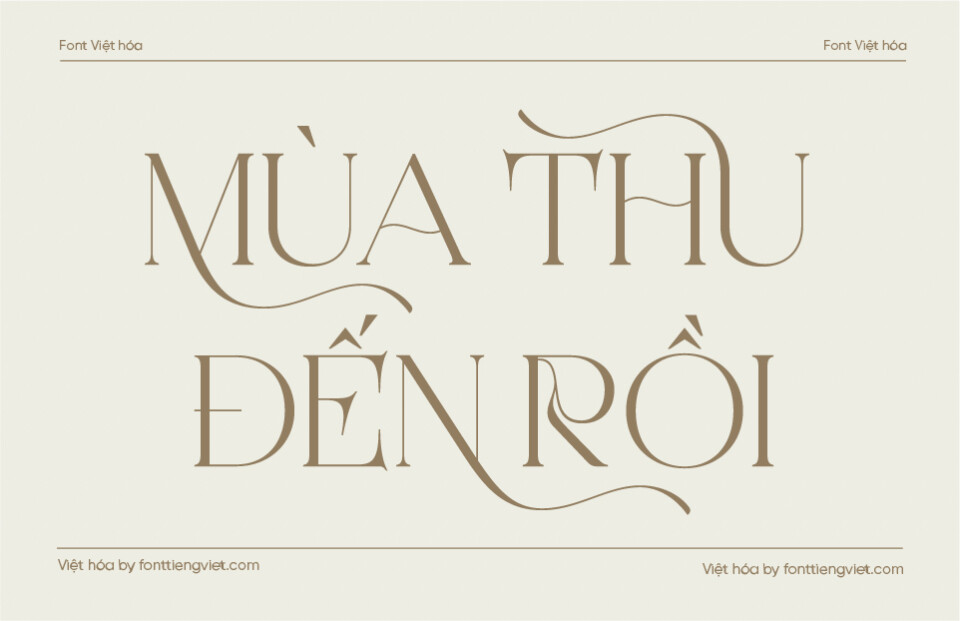
Tải Font Việt hóa 1FTV VIP Beauty Rovesa Miễn Phí Cho Thiết Kế Sang TrọngGiới thiệu về bộ Font Việt hóa 1FTV VIP Beauty Rovesa trong thiết kế đồ họaTrong thế giới thiết kế đồ họa hiện đại, việc lựa chọn một bộ chữ phù hợp đóng vai trò quyết định đến sự thành công của một tác phẩm nghệ thuật. Font Việt hóa 1FTV VIP Beauty Rovesa nổi lên như một lựa chọn hàng đầu cho những ai đang tìm kiếm sự kết hợp hoàn hảo giữa nét cổ điển và hơi thở đương đại. Đây là bộ Font Miễn Phí được tinh chỉnh kỹ lưỡng để phục vụ cộng đồng designer tại Việt Nam, đặc biệt là trong các lĩnh vực liên quan đến thời trang và làm đẹp. Với các đường nét thanh mảnh, uyển chuyển nhưng không kém phần chắc chắn, bộ chữ này mang lại cảm giác chuyên nghiệp và đẳng cấp ngay từ cái nhìn đầu tiên. Việc sử dụng các phông chữ đã được bản địa hóa giúp người dùng tránh được các lỗi hiển thị dấu tiếng Việt, từ đó đảm bảo tính thẩm mỹ cao nhất cho mọi dự án từ in ấn đến hiển thị kỹ thuật số.Những đặc điểm nổi bật của Font Việt hóa 1FTV VIP Beauty RovesaPhong cách thiết kế quý phái và tinh tếĐúng như tên gọi của mình, Font Việt hóa 1FTV VIP Beauty Rovesa mang trong mình DNA của sự sang trọng. Cấu trúc của các chữ cái được xây dựng dựa trên tỷ lệ vàng, tạo nên sự cân đối hài hòa cho thị giác. Các nét móc và điểm kết thúc của chữ được xử lý mềm mại, tạo ra một dòng chảy thị giác mượt mà khi trình bày các đoạn văn bản ngắn hoặc tiêu đề. Đối với các bạn học sinh và sinh viên ngành thiết kế, đây là công cụ đắc lực để biến những bài thuyết trình hay poster sự kiện trở nên thu hút và có chiều sâu hơn. Sự tinh tế này giúp bộ font không bị lỗi mốt theo thời gian, giữ vững giá trị sử dụng lâu dài trong kho tài nguyên của mỗi nhà thiết kế.Khả năng ứng dụng đa dạng trong nhiều dự ánMặc dù có tên gọi gắn liền với khái niệm làm đẹp, nhưng Font Việt hóa 1FTV VIP Beauty Rovesa lại có tính ứng dụng cực kỳ linh hoạt. Bạn có thể sử dụng bộ font này để thiết kế logo cho các thương hiệu cao cấp, làm thiệp mời đám cưới, hay thậm chí là trình bày bìa sách và tạp chí. Trong môi trường học đường, giáo viên có thể dùng font chữ này để tạo ra các chứng chỉ khen thưởng hoặc tài liệu giảng dạy có hình thức bắt mắt, giúp kích thích tinh thần học tập của học sinh. Sự rõ ràng của các ký tự giúp văn bản dễ đọc ngay cả ở kích thước nhỏ, điều mà không phải bộ font trang trí nào cũng làm được hiệu quả như vậy.Hướng dẫn cài đặt và lưu ý khi sử dụng Font Việt hóa 1FTV VIP Beauty RovesaCách cài đặt font chữ trên máy tính đơn giảnĐể bắt đầu sử dụng Font Việt hóa 1FTV VIP Beauty Rovesa, quy trình cài đặt vô cùng đơn giản và nhanh chóng. Sau khi tải tệp tin về máy, bạn chỉ cần giải nén thư mục, sau đó chuột phải vào các tệp định dạng .ttf hoặc .otf và chọn Install. Ngay lập tức, bộ font sẽ xuất hiện trong danh sách lựa chọn của các phần mềm phổ biến như Microsoft Word, Adobe Photoshop hay Canva. Điều này cho phép người dùng phổ thông cũng có thể tiếp cận và nâng tầm nội dung văn bản của mình một cách chuyên nghiệp nhất mà không cần quá nhiều kỹ năng kỹ thuật phức tạp.Lưu ý về bản quyền và mục đích sử dụngKhi sử dụng các bộ font được chia sẻ, người dùng cần lưu ý đến mục đích sử dụng cụ thể. Font Việt hóa 1FTV VIP Beauty Rovesa thường được cung cấp miễn phí cho các mục đích cá nhân và học tập. Nếu bạn dự định sử dụng cho các chiến dịch thương mại lớn của doanh nghiệp, hãy kiểm tra kỹ các điều khoản đi kèm hoặc liên hệ với tác giả gốc để đảm bảo quyền lợi hợp pháp. Việc tôn trọng bản quyền không chỉ là trách nhiệm đạo đức mà còn giúp cộng đồng sáng tạo tại Việt Nam phát triển bền vững hơn, khuyến khích các nhà thiết kế cho ra đời nhiều sản phẩm Việt hóa chất lượng hơn nữa trong tương lai.Kết luận về giá trị của bộ Font Việt hóa 1FTV VIP Beauty RovesaTổng kết lại, việc sở hữu bộ Font Việt hóa 1FTV VIP Beauty Rovesa trong bộ sưu tập cá nhân sẽ giúp bạn tự tin hơn khi thực hiện các dự án sáng tạo đòi hỏi tính thẩm mỹ cao. Với sự hỗ trợ đầy đủ các ký tự tiếng Việt và phong cách trình bày đẳng cấp, bộ chữ này xứng đáng là người bạn đồng hành tin cậy cho cả người mới bắt đầu và những chuyên gia lâu năm. Đừng bỏ lỡ cơ hội trải nghiệm sự khác biệt mà bộ font này mang lại cho tác phẩm của bạn. Hãy truy cập ngay vào Font Miễn Phí, Font Việt Hóa, Font Việt hóa 1FTV VIP Beauty Rovesa để cập nhật thêm nhiều tài nguyên thiết kế giá trị và độc đáo khác cho kho tàng sáng tạo của mình ngay hôm nay.
Font Việt hóa 1FTV VIP Beauty Rovesa